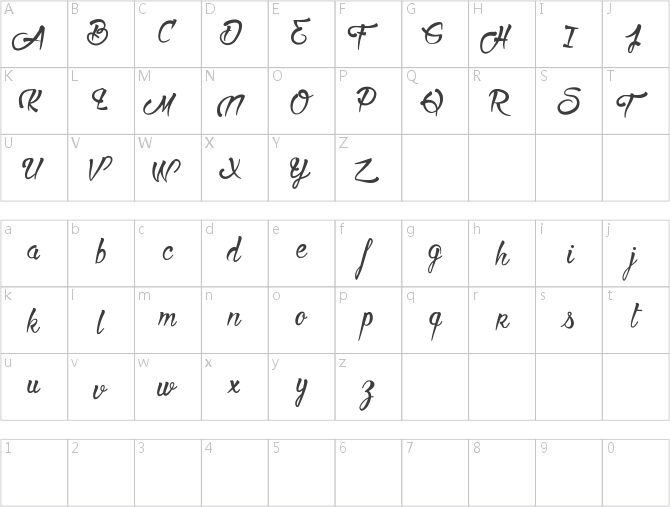
CF Samuel de Champlain 詳情頁
CF Samuel de Champlain
CF Samuel de Champlain字體字庫是一款讓人賞心悅目、百看不厭的英文字體,適合各類廣告和產品包裝設計應用,字體大小0.05MB,格式為ttf字體,上傳用戶是錦程正陽,作者/版權方為未知